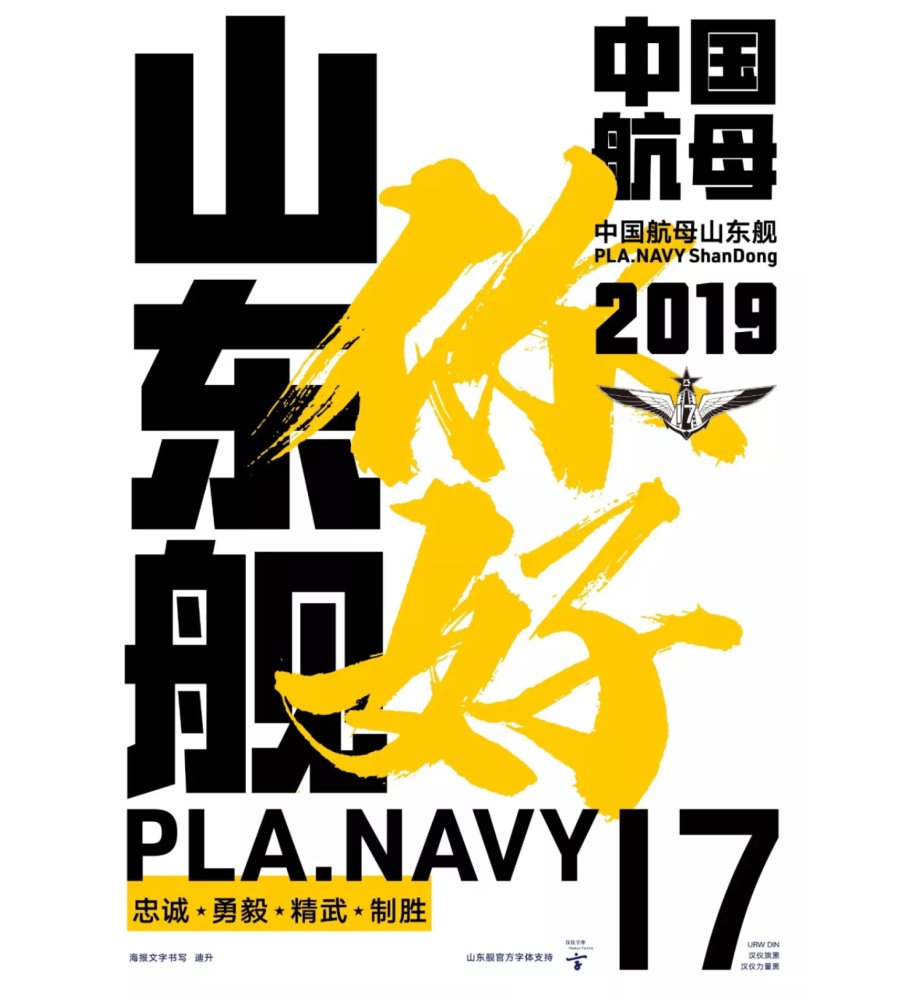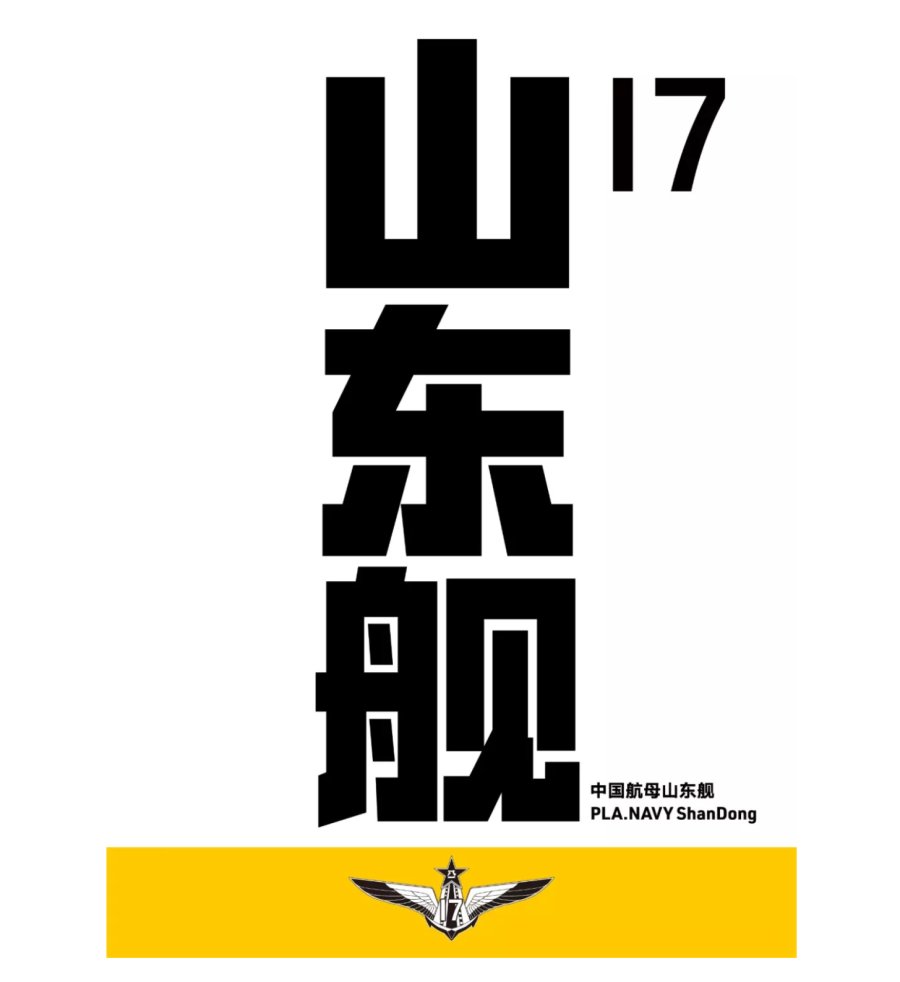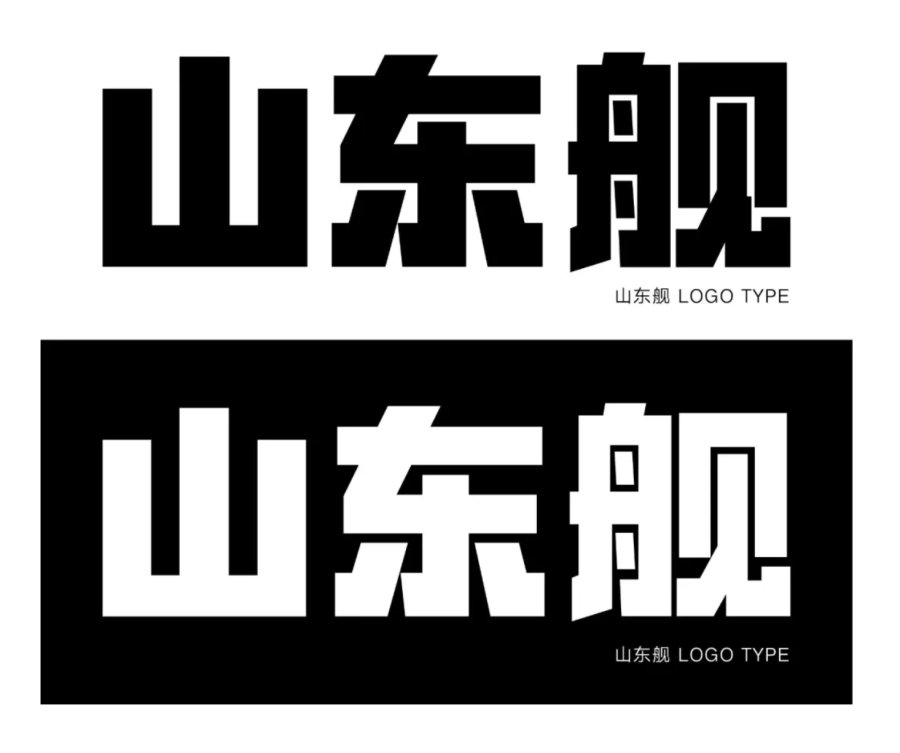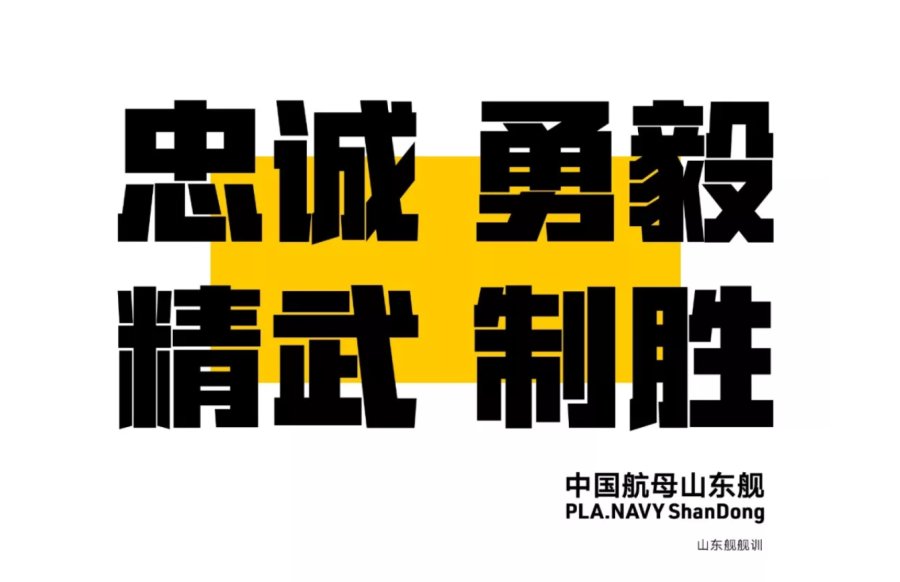
山东舰字体 字标欣赏
2019年12月17日,我国首艘国产航母 “山东舰” 正式入列服役!
汉仪字库作为国内最早从事字形字体设计、字库产品开发、汉字信息技术研究、提供汉字应用解决方案的专业字体团队,为山东舰的视觉识别系统提供了完整的字体服务支持。
山东舰的标志选取了一款刚劲有力的黑体 —— 汉仪力量黑,这是一款视觉冲击力很强的字体,线条平稳、粗壮、锋利,非常有重量感。这款字体的主创设计师刘宇对“山东舰”三个字的字面大小、笔画粗细以及字体重心做了针对性的修改,另外还在不同背景色下的显示进行了处理,笔画的交错和避让也更加明确,让标志在任何条件下都能够清晰易见。